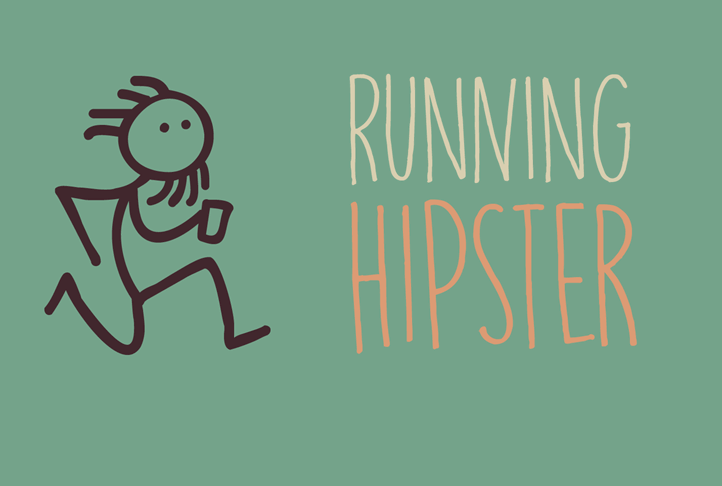
DK Running Hipster Font – Download Grátis
A DK Running Hipster Font é uma cópia minimalista do famoso estilo “Running Hipster”, que combina características manuscritas com uma pitada de graça desconcertada. Desenvolvida pelo designer David Kerkhoff, esta fonte handwritten oferece um toque único e irreverente para designers e criadores de conteúdo. Ela é especialmente adequada para criações que buscam se destacar em um ambiente de design contemporâneo. Se você está procurando por uma fonte manuscrita com características únicas e facilmente personalizáveis, a DK Running Hipster Font pode ser o seu ponto de partida perfeito. Embora seja gratuita para uso pessoal, é importante notar que não pode ser usada em jogos, aplicativos ou softwares comerciais. Se você precisa de uma licença específica para esses fins, David Kerkhoff oferece uma ampla gama de opções em sua plataforma oficial, www.hanodedfonts.com. Além disso, há uma seção FAQ disponível no arquivo zip fornecido, para ajudá-lo a responder a qualquer dúvida que possa surgir durante o uso da fonte. Na página de download desta fonte, você encontrará um conjunto completo e perfeitamente gerenciado de caracteres, incluindo a numeração completa e adicional material exclusivo do designer. Como sempre, as preferências individuais e estilos pessoais são importantes, e a DK Running Hipster Font oferece o poder para expressá-los através da escrita.